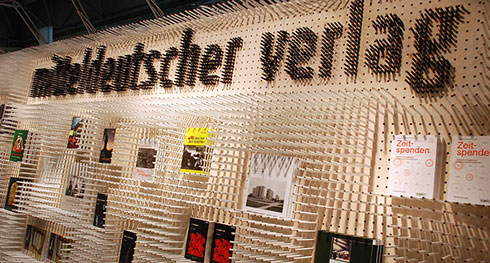
In Halle 5 der Leipziger Buchmesse stiftet der Mitteldeutsche Verlag die Besucher im wahrsten Sinne des Wortes zum Lesen an. Aus 15.000 Bleistiften sind Regal, Display und Schriftzug konstruiert, nach einem Konzept von Johannes Albert und Helmut Stabe. Als Firmenschrift dient Yanones Frühwerk Kaffeesatz, inzwischen unter dem Namen FF Kava professionell zur Familie ausgebaut (siehe auch Kaffeesahne von Yanone: die neue FF Kava). Der Buchgestalter Helmut Stabe über die manuelle Verfeinerung des Schriftzuges: »Wir haben mit 1603 Bleistiften ein Analog-Hinting durchgeführt. Es wackelt zwar hier und da ein wenig, aber die Hausschrift des Verlags ist gut zu erkennen.«
Muss natürlich nachher vor Ort nochmal visuell überprüft werden. Ich platze vor Neugier. Verrückt, wie gut die Schrift schon hier zu erkennen ist.